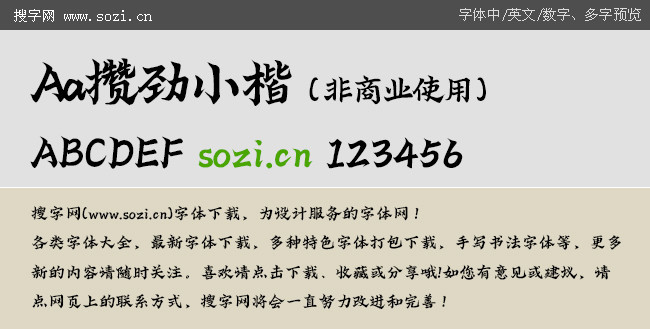
Aa攢勁小楷
搜字網(wǎng)給大家提供一款A(yù)a攢勁小楷(非商業(yè)使用)中文字體下載,該字體是一款手寫(xiě)風(fēng)格的書(shū)法字體,字體書(shū)寫(xiě)流暢,瀟灑大方,具有很好的視覺(jué)感,適用于平面宣傳設(shè)計(jì)、網(wǎng)頁(yè)設(shè)計(jì)、海報(bào)設(shè)計(jì)等應(yīng)用(此字體為個(gè)人非商用版,商用可以聯(lián)系QQ:1006760504)。